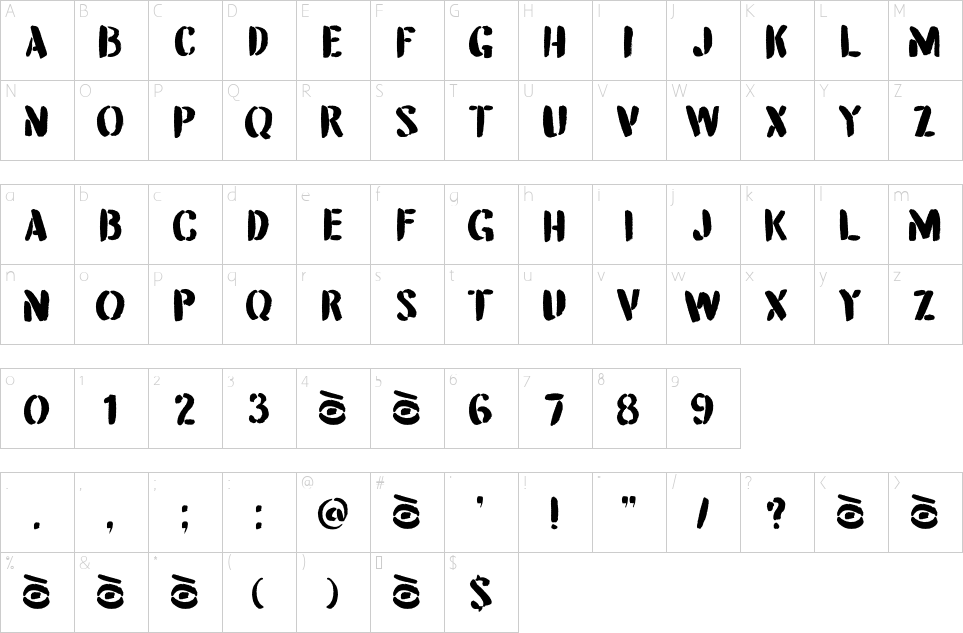
A fonte DK Attention Seeker é uma opção moderna e chamativa para aqueles que buscam adicionar destaque ao seu design digital. Desenvolvida pelo designer Hanoded, essa fonte é projetada para destacar sua mensagem de maneira impactante em ambientes digitais diversos, desde redes sociais até websites e impressões digitais. Com um design inovador e arredondado que se sobressai, DK Attention Seeker foi projetada para ser usada no texto de destaque ou em títulos importantes. Se você está procurando por uma fonte capaz de atrair a atenção do seu público-alvo, esta seria uma escolha inteligente. Seu formato Windows e Mac permitirá que você utilize essa fonte em qualquer dispositivo e plataforma digital, garantindo que seu design esteja sempre atualizado e relevante. Com uma instalação fácil e sem custos, DK Attention Seeker se torna uma excelente opção para designers gráficos, webmasters e criadores de conteúdo que querem aumentar a visibilidade do seu trabalho. A fonte já foi baixada 6,488 vezes, demonstrando sua relevância no mercado.